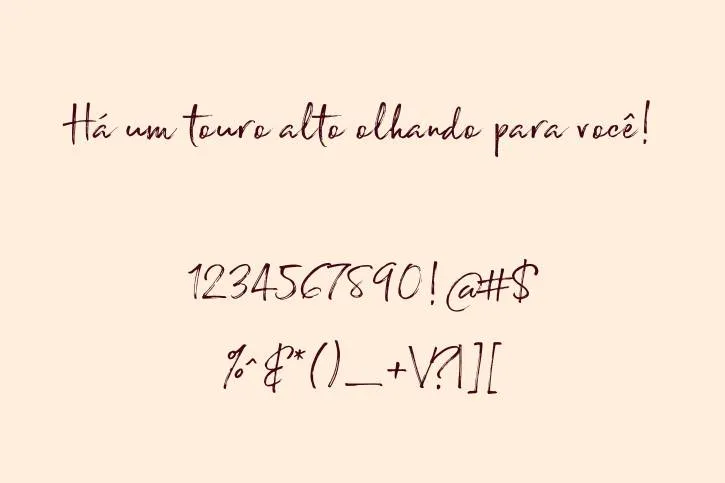
A fonte Broadcast Matter é uma fonte moderna e expressiva conhecida por seu estilo pincel marcante e foi projetada por StereoType. Com características fluidas e naturais, esta fonte transmite uma sensação de movimento e energia. É ideal para projetos que buscam um toque de dinamismo e personalidade. Seu design único e elegante o torna uma escolha popular entre os designers.
Possui muitas fontes semelhantes que estão disponíveis em nossa plataforma, como a Fonte Soul, que também é uma fonte de pincel. Seu estilo de pincel fica evidente em seus traços fluidos e orgânicos, que lembram uma escrita feita com pincel. Isso confere à fonte uma aparência artesanal e artesanal, agregando um elemento de autenticidade e charme aos projetos em que é utilizada.
Sua aparência única e distinta faz com que ela se destaque entre outras fontes, tornando-a uma escolha popular para materiais de marketing. Sua legibilidade é uma de suas principais características. Apesar do seu estilo caligráfico, é facilmente legível em tamanhos maiores e em diferentes contextos de design.
Recurso Principal da Fonte Broadcast Matter
A principal característica é o seu estilo caligráfico expressivo e dinâmico. Com traços fluidos e naturais, essa fonte transmite sensação de movimento e energia, sendo ideal para projetos que buscam um toque de dinamismo e personalidade. Você pode usar a fonte Umba Soft combinando-a com esta fonte. Seu design único e elegante o torna uma escolha popular entre designers que desejam adicionar um toque de originalidade ao seu trabalho.
Família de Fontes Broadcast Matter
- Broadcast Matter Regular
Aplicações da Fonte Broadcast Matter
- Cabeçalhos de sites e blogs com um toque moderno e elegante.
- Materiais promocionais, como cartazes e banners, para chamar a atenção.
- Convites de eventos, dando um ar sofisticado aos detalhes.
- Logotipos e marcas, transmitindo uma sensação de contemporaneidade.
- Materiais impressos, como cartões de visita e folhetos, para destacar informações.
- Design de embalagens, proporcionando uma estética diferenciada.
- Redes sociais, criando posts visualmente atraentes.
- Projetos de design de interiores e decoração, para personalizar elementos.
- Publicações digitais e impressas, mantendo uma estética consistente.
Qual é a fonte da fonte Broadcast Matter?
A fonte Broadcast Matter é uma fonte moderna e expressiva, conhecida por seu estilo de pincel marcante e foi projetada pela StereoType.
Qual é a principal característica da fonte Broadcast Matter?
Possui características fluidas e naturais, que conferem aos designs sensação de movimento e energia.